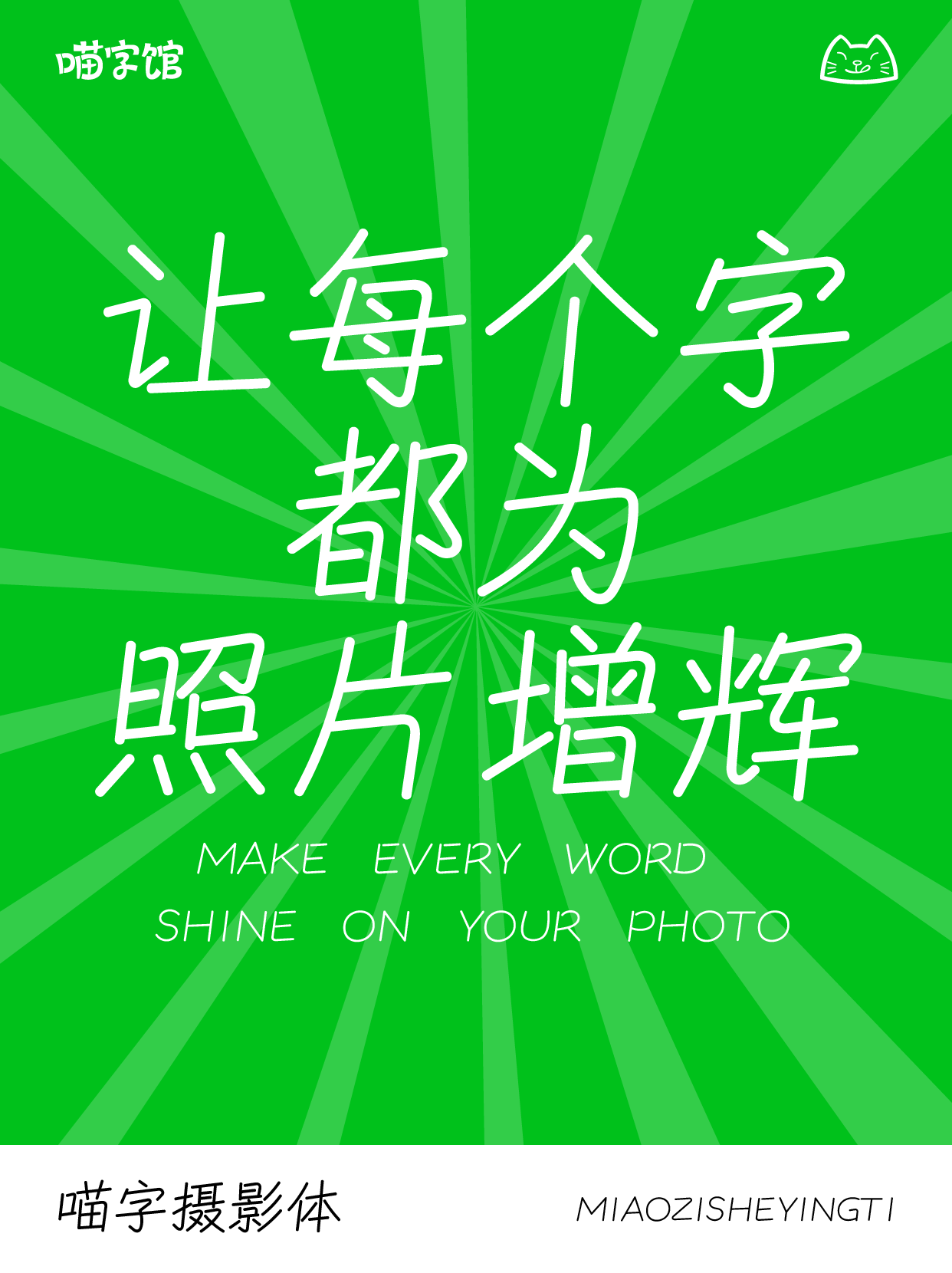
喵字摄影体,
喵字摄影体是一款定位于摄影行业的定制级字库产品。该字融合传统楷书的间架穿插特点与现代线性字体的笔画特点,来为摄影行业提供新的市场用字解决方案,力求帮助使用者营造清新自然的设计氛围。
励字玉树临风简,
瘦长的字形,修长端正,风格朴实敛静,拙中见巧,散发着质朴的美感。适合广告设计、平面设计、印刷包装、正文标题等。
励字超级勇士简 纤细,
以黑体作为基础,起收笔采用斜切的方式,将部分笔画做了简化和省略。选择最为纤细的笔画字重,使字体具有清透柔和美感。